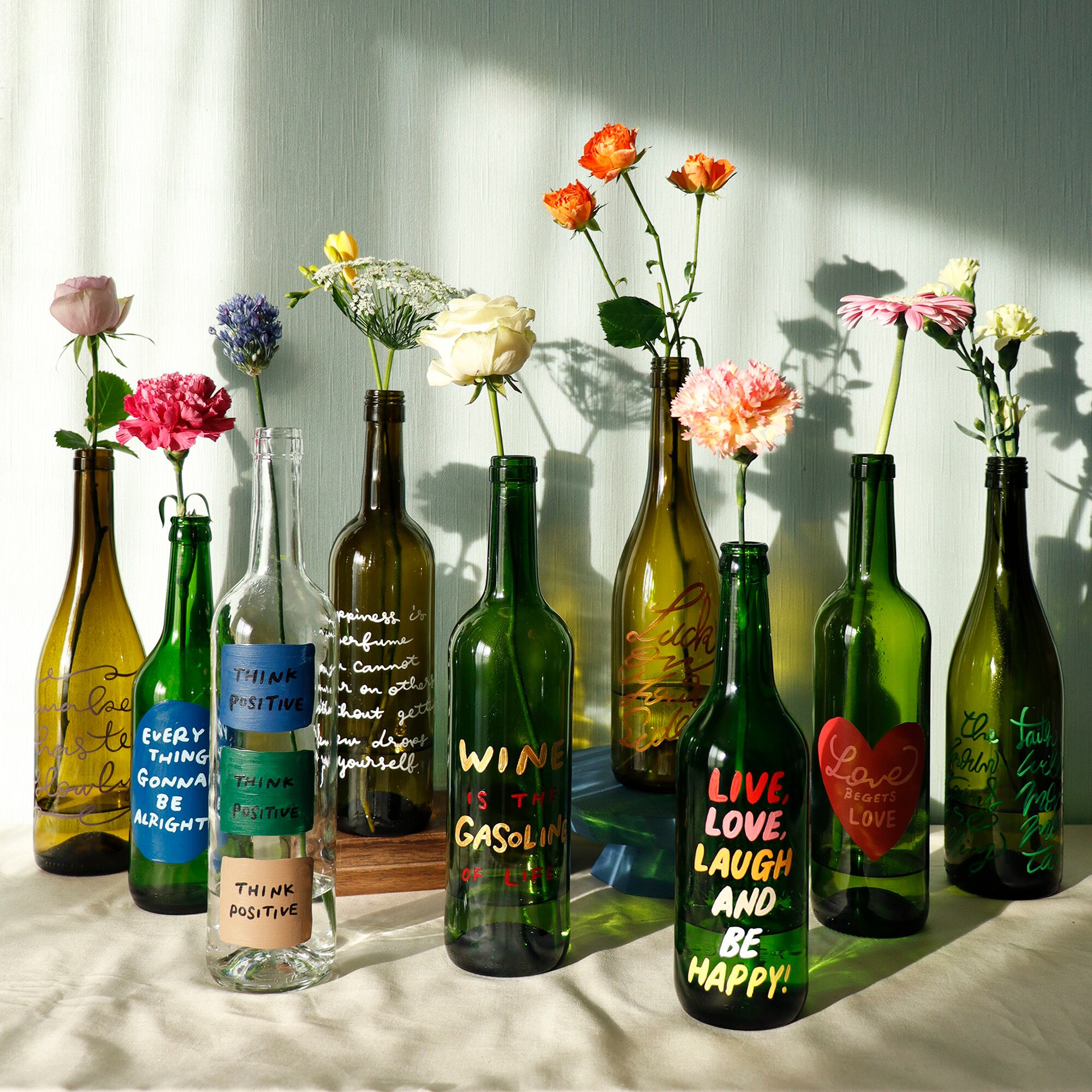
【BOTTLE PAINT ART】wine is the gasoline of life 01
ワインボトルにペイントした、気軽に飾れるアートな作品が登場!
Wine is the gasoline of life
ワインは人生のガソリンだ
ワイン好きな方にきっといるのでは?という言葉描いてます。ワイン大好きな方、ぜひ^ ^
光が入るとこに置くと、瓶の色とともに文字も影になって素敵ですよ!!